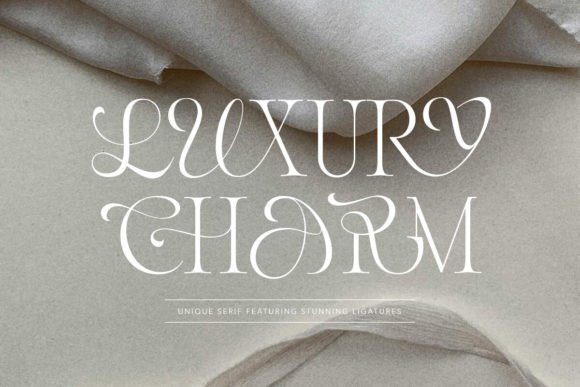
Luxury Charm
Conçu avec précision, Luxury Charm offre des vecteurs nets, une typographie fluide et une licence commerciale pour une tranquillité d'esprit.